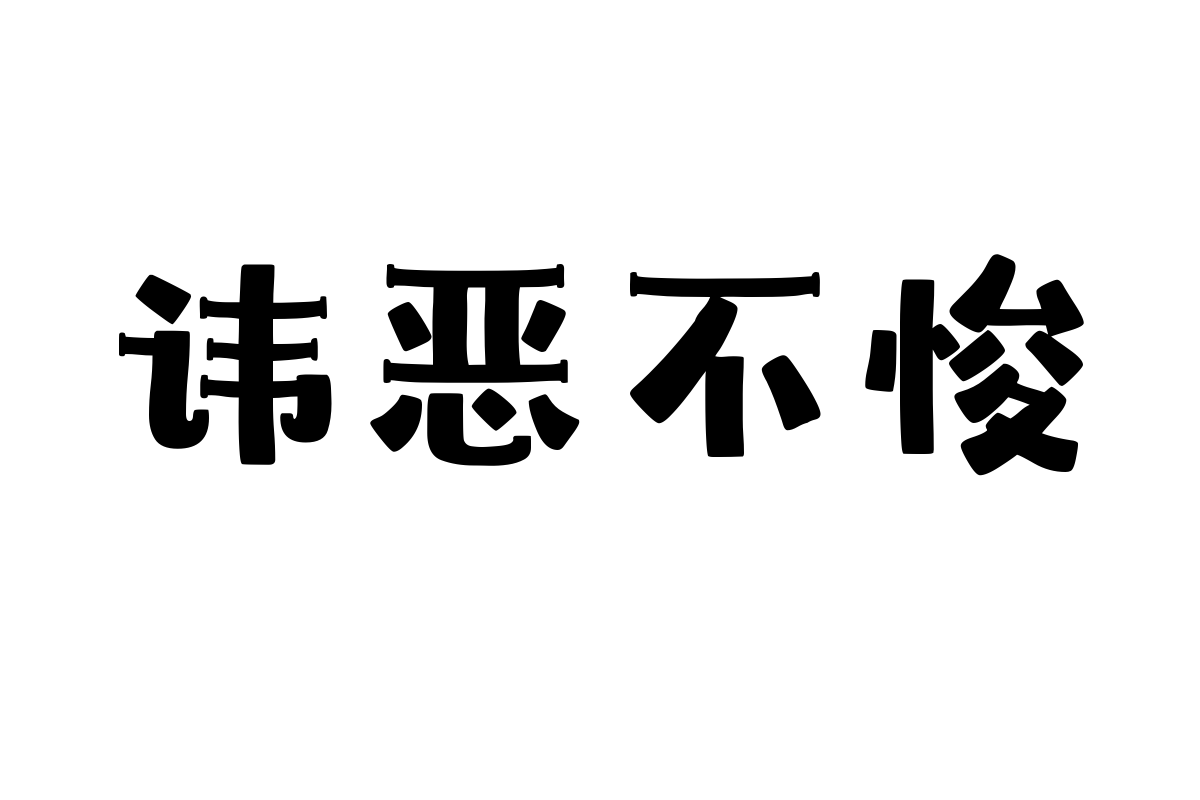
山海小顽童W是一款具有独特艺术风格的字体,它结合了传统书法和现代设计元素,创造出一种既古典又时尚的视觉效果。这款字体适用于各种设计场景,包括标志、广告、包装等,能够为作品增添独特的艺术气息。
山海小顽童W的特点在于其笔画流畅、结构紧凑,给人一种简洁而不失优雅的感觉。它的字形呈现出一种自然生长的状态,仿佛在山水之间自由漫步,给人一种宁静而深远的印象。同时,这款字体也融入了一些现代设计的元素,使得它在保持传统的同时,也能够适应现代的设计需求。
总的来说,山海小顽童W是一款非常适合用于各种设计场景的字体,无论是用于品牌标识还是其他商业宣传材料,都能够展现出独特的艺术魅力。